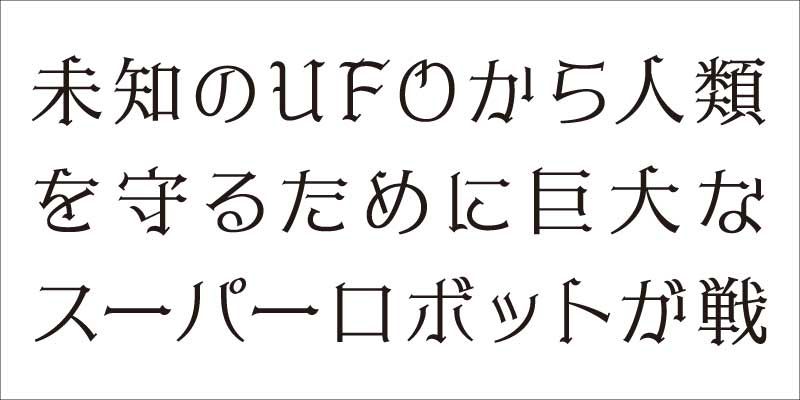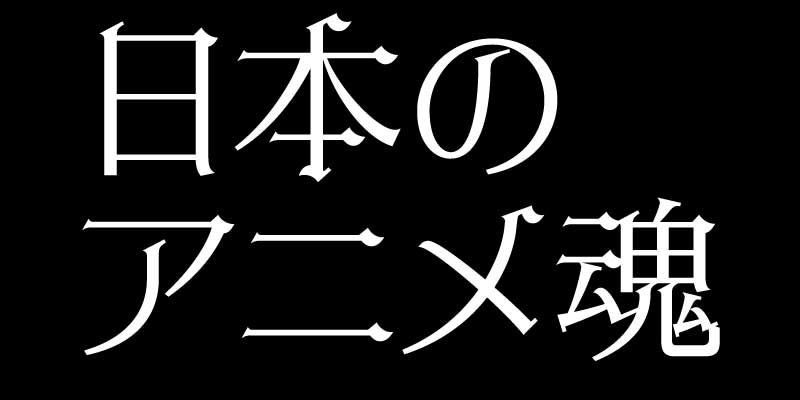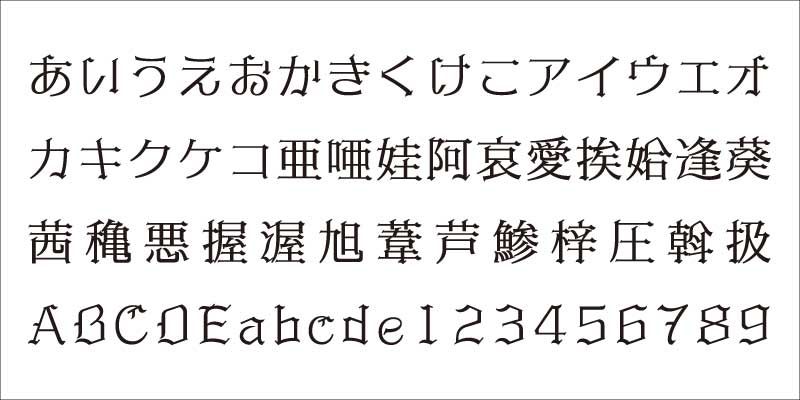
独特な始端の線、ハライ曲線、ウロコの三角形の末端のある強固なバックボーンを持つ書体です。 デザインに試行錯誤を多く重ねて、独特な輝きを放つ日本語書体が生まれました。
視覚デザイン研究所 (VDL) は、文字の持つ伝統的な美しさを損なうことなく、斬新でありながらも「造形の美的バランス」と「文字の可読性」この両立をコンセプトとした、新しい表情の日本語フォントを創出しています。VDL は、フォント選びはデザインの一部だと考えています。個性を美しく強く主張する『VDL デザイナーズフォント』が、あなたのデザインと融合し新しい表現が生まれることを願っています。